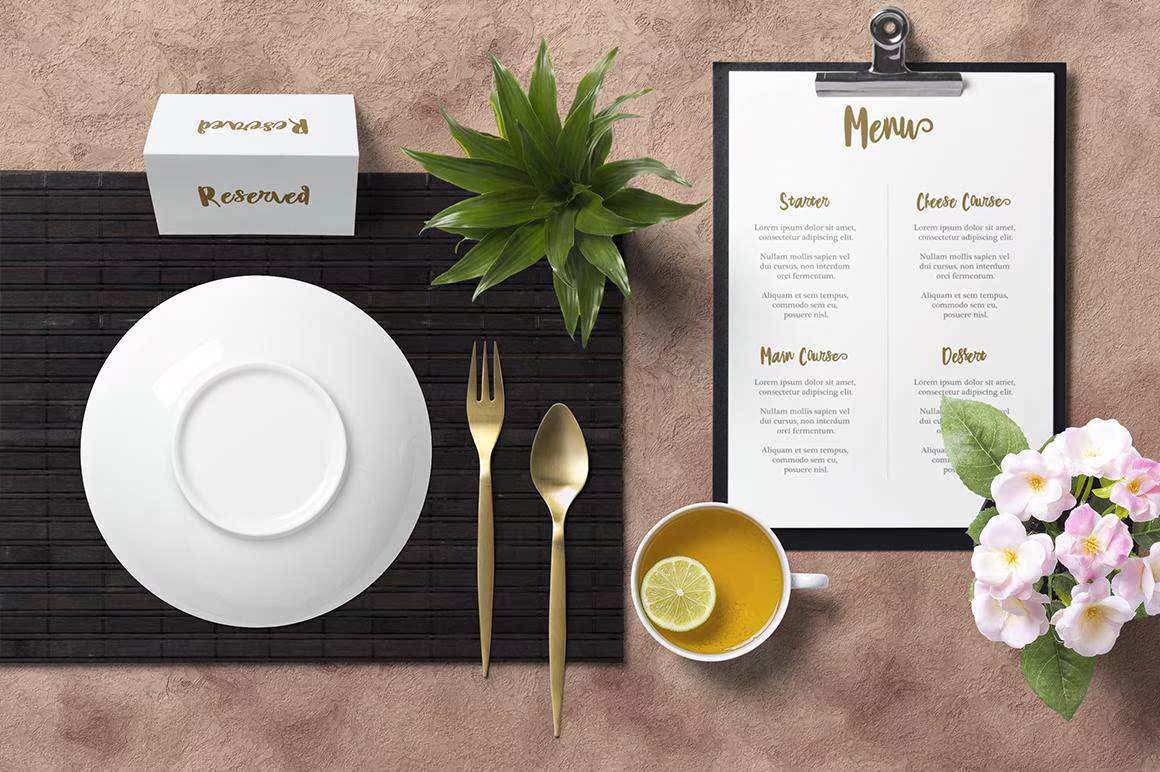
WirePop是一种现代化的PCallographyscript手写体Tenstyle。通过手写和书写创建,使此字体看起来简洁、优雅、自然,适合任何需要手写文本处理的项目。可用于任何不同的项目,如徽标和品牌、邀请、婚礼设计、社交成本、广告、产品包装、,LabelandMore.WirePop是一种现代化的PCallographyScript手写体Tenstyle。通过手写和书写创建的字体使该字体看起来更为简洁、优雅、自然,适用于任何需要手写文本处理的项目。可用于任何不同的项目,如徽标和品牌、邀请、婚礼设计、社交成本、广告、产品包装、,Labelandmore。